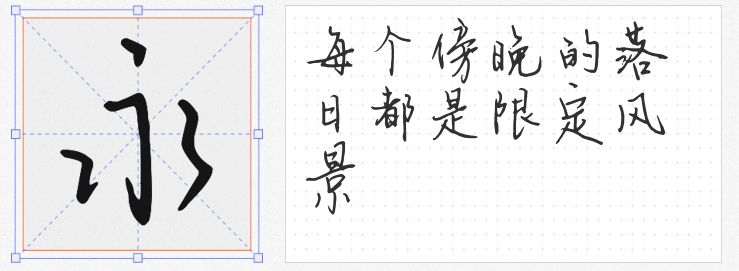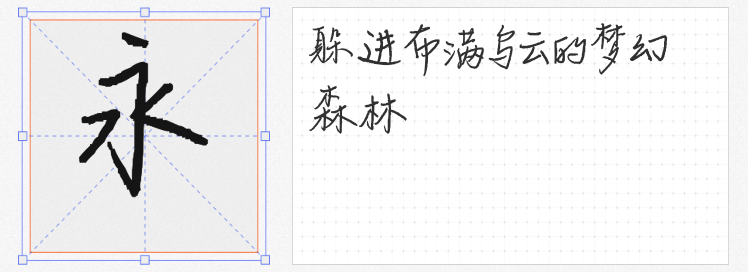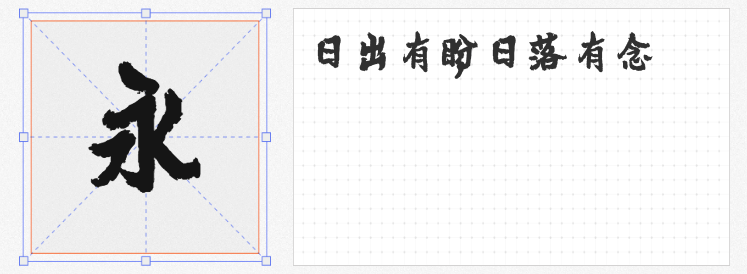
在商业设计中,一款兼具视觉冲击力与实用性的字体往往能成为作品的核心亮点。本文精选四款免费可商用的超粗黑体变体——它们以手写风格为基底,却突破传统黑体的厚重感,通过独特的笔触与结构为设计注入鲜活个性,尤其适合标题、海报、品牌视觉等场景。
1. 云峰林桥体
这款字体以严谨的笔画结构打破手写字体易显松散的刻板印象。每一笔都如刻刀雕琢般利落,横竖转折处保留自然的手写弧度,既保留了黑体的力量感,又通过微妙的粗细变化传递温度。适用于科技产品海报、教育类宣传物料,或需要传递专业感与人文关怀的混合风格设计。
2. 她屿山海
若说云峰林桥体是理性的工整,她屿山海则是感性的诗篇。字体以轻盈的笔触模拟日记本上的随性书写,字间距宽松,重心微微起伏,营造出呼吸感十足的视觉节奏。其独特的文艺气质使其成为文创产品包装、咖啡厅菜单、独立音乐专辑封面的理想选择,尤其适合需要传递温暖与故事感的场景。
3. 栗壳坚坚体
这款字体以超细笔触重构黑体骨架,通过流畅的曲线与锐利的收笔形成鲜明对比。看似纤弱却暗藏张力,在保持高辨识度的同时,为画面留出更多呼吸空间。其极简特质使其在网页标题、移动端界面、品牌LOGO等需要远距离识别的场景中表现卓越,亦能通过叠加材质纹理打造高级感。
4. 云峰游戏标题
专为高强度视觉竞争场景而生,这款字体以夸张的笔画粗细对比与动态倾斜角度,瞬间抓住观众眼球。字体内置的“破坏性”细节——如断裂笔触、墨点飞白——赋予其赛博朋克式的粗粝质感,完美适配游戏LOGO、影视片头、运动品牌广告等需要强烈情绪传达的领域。